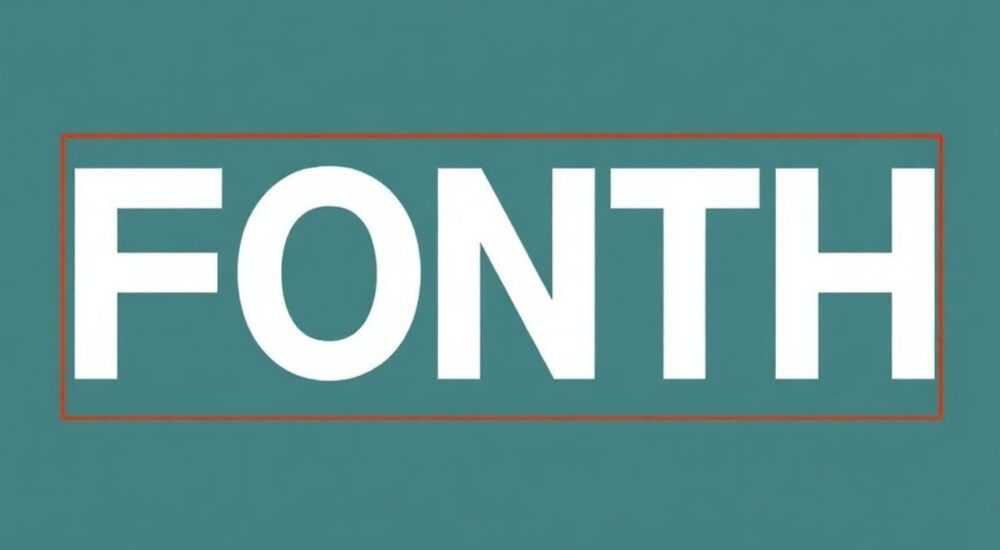
Как определить шрифт в фотошопе с картинки
Определить шрифт на изображении в Photoshop можно как вручную, с помощью визуального анализа и встроенных инструментов, так и с привлечением сторонних сервисов распознавания шрифтов. Наиболее эффективный подход — комбинация инструмента Match Font в Adobe Photoshop (доступен с версии CC 2015) и онлайн-сервисов вроде WhatTheFont, Font Squirrel Matcherator или Identifont. Главная рекомендация: перед анализом убедитесь, что текст на изображении чёткий, крупный и хорошо контрастирует с фоном.
В современной графической среде дизайнеры, редакторы и маркетологи часто сталкиваются с необходимостью воссоздать визуальный стиль, основываясь только на готовом изображении. Одной из ключевых задач при этом становится идентификация используемого шрифта. Несмотря на широкий выбор типографических решений, точное попадание в оригинальный стиль без знания названия гарнитуры может занять много времени. Adobe Photoshop, будучи лидером среди графических редакторов, предлагает встроенные и сторонние решения для решения этой проблемы. Однако многие пользователи до сих пор полагаются на визуальное сравнение или перебор шрифтов вручную, что неэффективно и трудоёмко.
С развитием технологий компьютерного зрения и машинного обучения процесс распознавания шрифтов стал значительно проще. Современные алгоритмы способны анализировать форму символов, их пропорции, засечки, начертание и другие типографские характеристики, чтобы подобрать максимально близкие аналоги. Важно понимать, что ни один метод не гарантирует 100% совпадения, особенно если текст размыт, повёрнут, деформирован или имеет сложные эффекты. Тем не менее, при соблюдении определённых условий точность распознавания может достигать 90% и выше.
Как использовать Match Font в Photoshop
Функция Match Font — одна из самых мощных и недооценённых возможностей Adobe Photoshop. Она была внедрена в 2015 году и с тех пор регулярно обновляется. Этот инструмент позволяет автоматически определять шрифт на изображении, анализируя выделенный фрагмент текста. Для работы требуется подключение к интернету и аккаунт Adobe Creative Cloud.
Чтобы воспользоваться Match Font, выполните следующие шаги:
- Откройте изображение в Photoshop с текстом, шрифт которого нужно определить.
- Выберите инструмент «Прямоугольная область» (M) и выделите участок с текстом. Старайтесь захватить как можно больше символов, желательно — целое слово или предложение.
- Перейдите в меню Тип → Определить шрифт (Match Font).
- Photoshop проанализирует выделенную область и предложит список похожих шрифтов из своей базы данных.
- Проверьте результаты: каждый найденный шрифт отображается с примером начертания и указанием уровня соответствия.
Система сравнивает форму букв с более чем 20 000 шрифтами из библиотеки Adobe Fonts. Результаты сортируются по степени схожести. Вы можете установить понравившийся шрифт одним кликом, если он доступен в подписке Creative Cloud. Даже если точного совпадения нет, функция помогает сузить круг поиска до нескольких вероятных кандидатов.
Когда Match Font даёт сбой
Несмотря на мощь технологии, Match Font не всегда срабатывает идеально. Причины могут быть следующими:
- Текст слишком маленький или размытый.
- Изображение содержит наклонённый, искажённый или повёрнутый текст.
- На картинке используется кастомный, рукописный или декоративный шрифт, отсутствующий в базе Adobe.
- Выделенная область включает не только текст, но и сложный фон, мешающий анализу.
В таких случаях рекомендуется предварительно обработать изображение: увеличить масштаб, применить резкость (Filter → Sharpen), удалить фон или выделить текст с помощью масок. Это повысит точность распознавания.
Лучшие онлайн-сервисы для определения шрифтов
Если встроенные средства Photoshop не дали результата, на помощь приходят специализированные онлайн-инструменты. Они используют более продвинутые алгоритмы и огромные базы данных, включая редкие и бесплатные шрифты.
Как пользоваться WhatTheFont
Сервис от MyFonts — один из самых популярных. Процесс прост:
- Загрузите изображение через интерфейс сайта.
- Система автоматически обнаруживает текстовые области.